2023 年 Instagram 的 30 種最佳字體(免費和付費)
在本文中,我們整理了 30 種最適合 Instagram 的字體列表,它們將使您的帖子栩栩如生。 無論您是圖形設計師還是社交媒體經理,這些字體都將幫助您創建觀眾喜愛的令人驚嘆的視覺效果。
您是否知道正確的字體可以提高參與度甚至促進銷售? 根據創意市場的一項研究,使用獨特且引人注目的字體可以提高產品和服務的感知價值。
因此,如果您想改進 Instagram 遊戲,就必須投資優質字體。
言歸正傳,讓我們深入了解 Instagram 排名前 30 的字體的綜合列表,它們將使您的設計更上一層樓。
Instagram 的最佳高級字體
當談到提升 Instagram 內容的設計時,優質字體可以發揮重要作用。 我們的最佳高級字體列表提供了多種選項,可將您的視覺效果提升到一個新的水平。 查看我們精心挑選的完美字體,以增強您的 Instagram 動態。
普里西拉
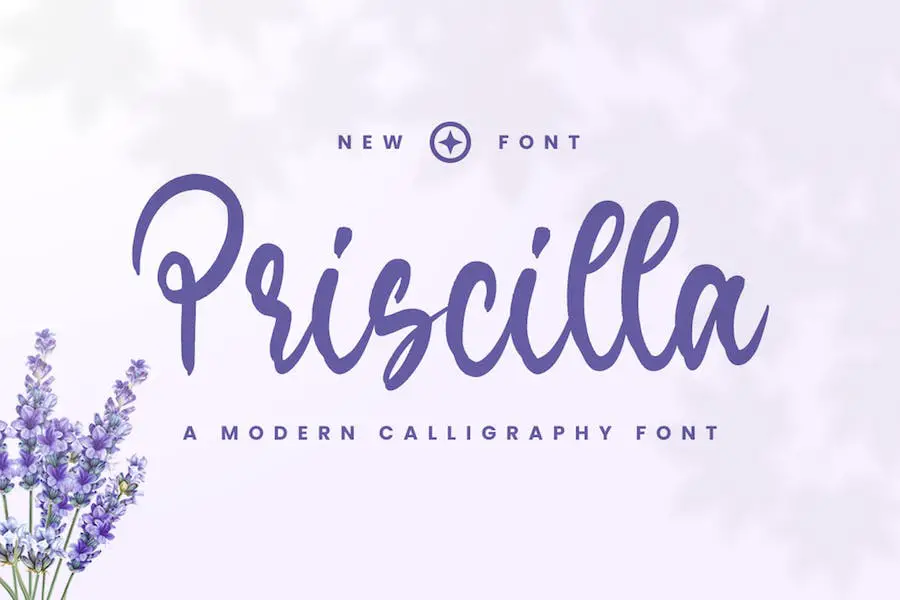
Priscilla 是一種現代而優雅的腳本字體,非常適合徽標、品牌、邀請函和社交媒體帖子等各種應用。
憑藉其精緻的外觀和優雅的風格,Priscilla 一定會讓您的項目脫穎而出。 您可以將它用於婚禮設計、文具等等。 該字體具有 OTF 和 TTF 格式,並包含 PUA 編碼字符,無需額外的設計軟件即可完全訪問。
因此,無論您是平面設計師、營銷人員還是博主,您都會喜歡 Priscilla 的精緻和多功能性。 對於任何想要為自己的工作增添一絲優雅氣息的人來說,這是一個絕佳的選擇。
與 Priscilla 一起,您可以將您的想法轉化為精美的創作,並給您的客戶和觀眾留下深刻的印象。 那麼今天就來嘗試一下吧!
俄克拉荷馬州
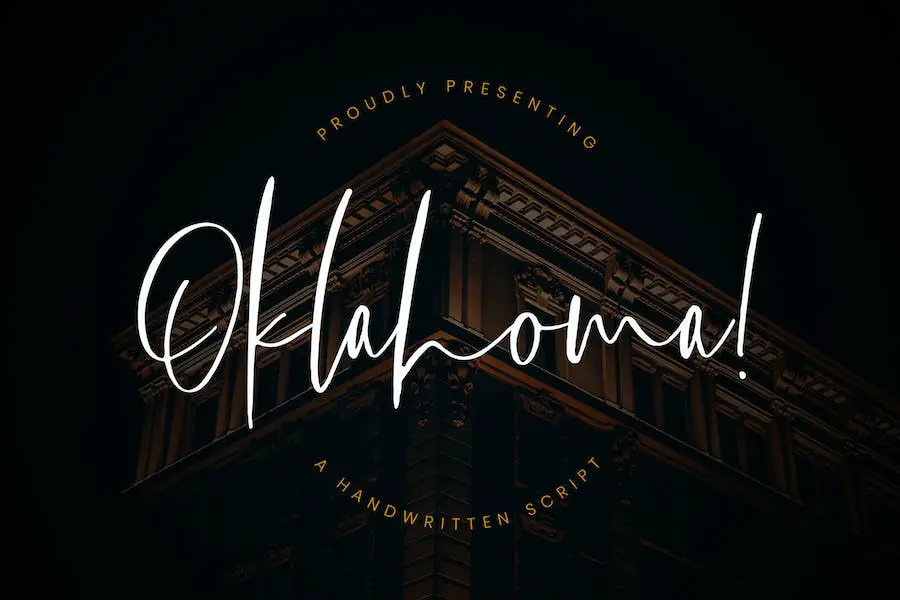
Oklahoma 是一種時尚而現代的字體,為您最新的設計項目增添優雅和優雅的感覺。 它具有自然的手寫腳本和大量的字形和連字,帶來個性化的感覺。
借助多語言支持,您可以使用 Oklahoma 進行各種品牌項目、徽標設計、婚禮請柬、社交媒體帖子、廣告和產品包裝。
無論您是為 Google Instagram 字體、Adobe Instagram 字體、Word Instagram 字體、現代 Instagram 字體還是 Instagram 時尚字體創建內容,Oklahoma 都能提供獨特而精緻的外觀。
雅瑪塔
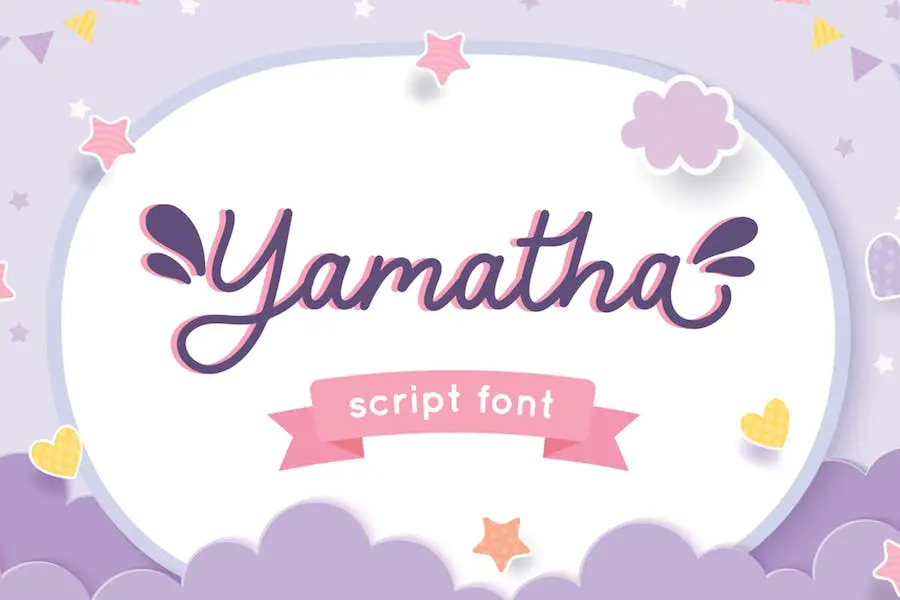
Yamatha 是一種斜體樣式的腳本字體,非常適合為您的設計項目增添額外的優雅氣息。 它的開頭和結尾花體結合在一起使字母更加美麗。 該字體還包括連字和多語言支持。
Yamaha 非常適合婚禮促銷、品牌推廣、徽標、邀請函和文具。 它也非常適合社交媒體帖子、產品包裝、商品、博客設計、遊戲標題、可愛的風格設計以及書籍或封面標題。
對於希望為自己的作品增添一絲精緻和美麗的設計師來說,這種字體是一個不錯的選擇。 憑藉其廣泛的用途和功能,Yamatha 是任何為 Instagram 和其他社交媒體帖子尋找現代時尚字體的人的必備之選。
鹽
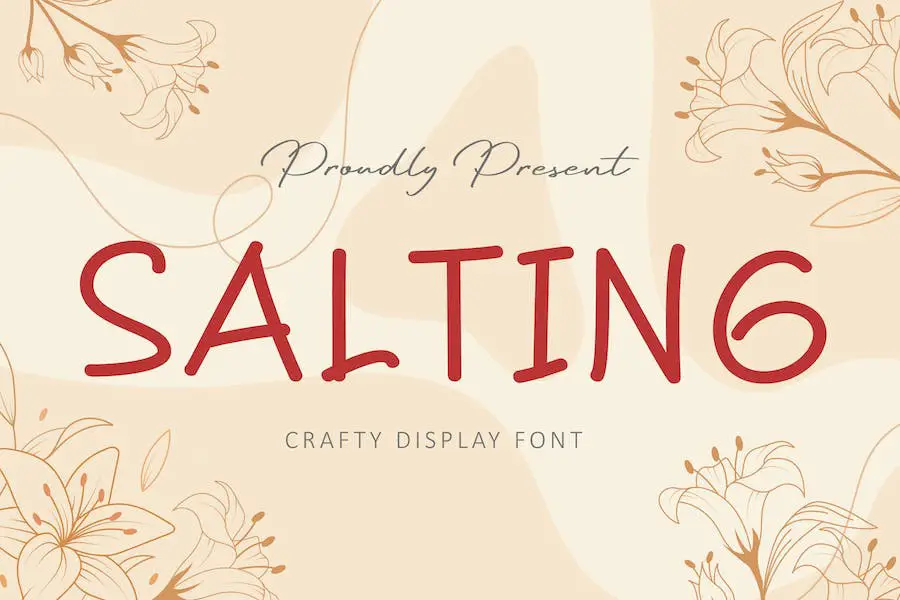
Salting 是一種精緻而奢華的腳本字體,專為社交媒體(尤其是 Instagram)設計。 它是為您的 Instagram 帖子增添優雅氣息、製作令人驚嘆的婚禮請柬或設計精美的文具藝術品的完美選擇。
憑藉其時尚和現代的吸引力,這種字體一定會讓您的內容脫穎而出。
通過 Salting,您將可以使用一系列時尚的字體,這些字體可以輕鬆生成並用於您的 Instagram 帖子。 無論您是在尋找小字體以在標題中容納更多文本,還是想嘗試不同的現代字體,此字體生成器都能滿足您的需求。
貝林多
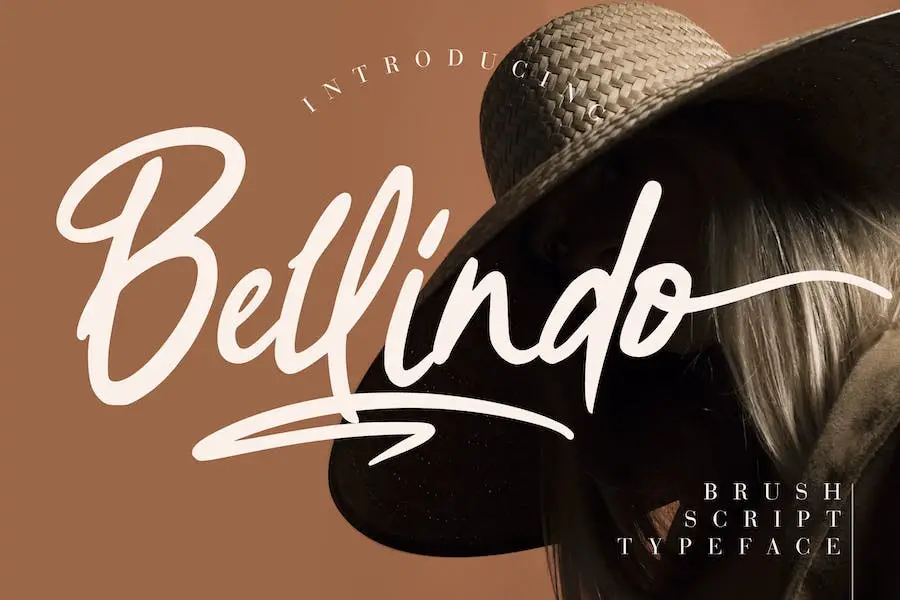
Bellindo 是一種天然的畫筆字體,稱為 It Brush Script,散發著優雅和優雅的氣息。 憑藉其驚人的功能,這種字體非常適合您最新的設計項目。
它完美匹配您的品牌、電影標題、書名、社交媒體、婚禮請柬、卡片以及您能想到的任何其他場合。
您可以享受其令人驚嘆的功能,例如數字、連字、標點符號、花體和標準字符。 此外,您還可以在 Adobe Illustrator、Adobe Photoshop 和 Adobe InDesign 中訪問它。 它還支持多種語言的多語言字符。
嘿比安查
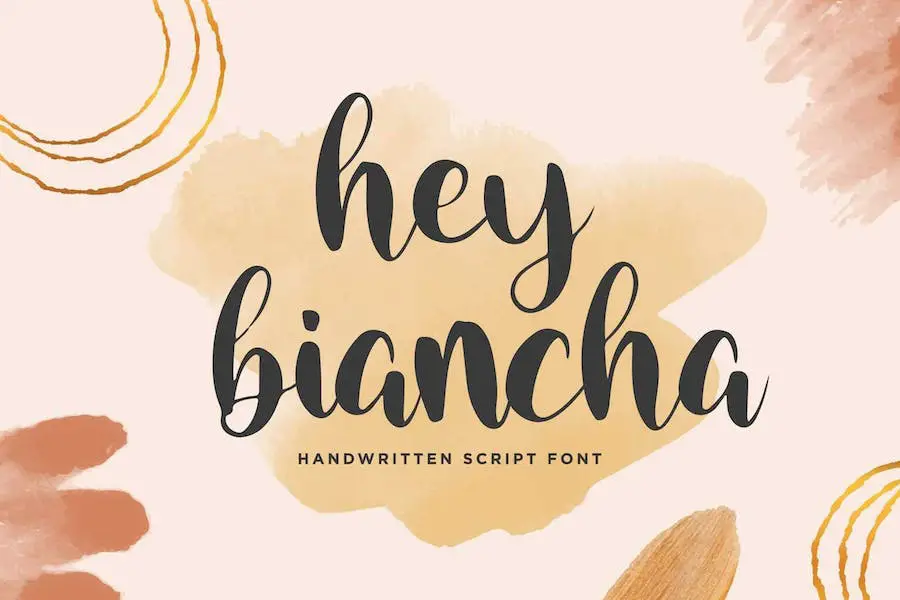
Hey Biancha 是一種手寫腳本字體,非常適合社交媒體帖子、品牌、引言、博客文章、T 卹設計、徽標和邀請函。 憑藉其現代而獨特的風格,在您的項目中使用這種字體將為您的項目帶來引人注目的吸引力。
它提供多語言支持,使您能夠毫無困難地用不同語言定制設計。
使用 Hey Biancha 是一種獨特的方式來改進社交媒體帖子的 Instagram 字體,並創建脫穎而出的現代 Instagram 字體。
其手寫設計為設計增添了個人風格,使其更具吸引力。 嘗試一下 Hey Biancha,用你聰明而富有創意的設計給你的觀眾留下深刻的印象!
卡斯頓維拉
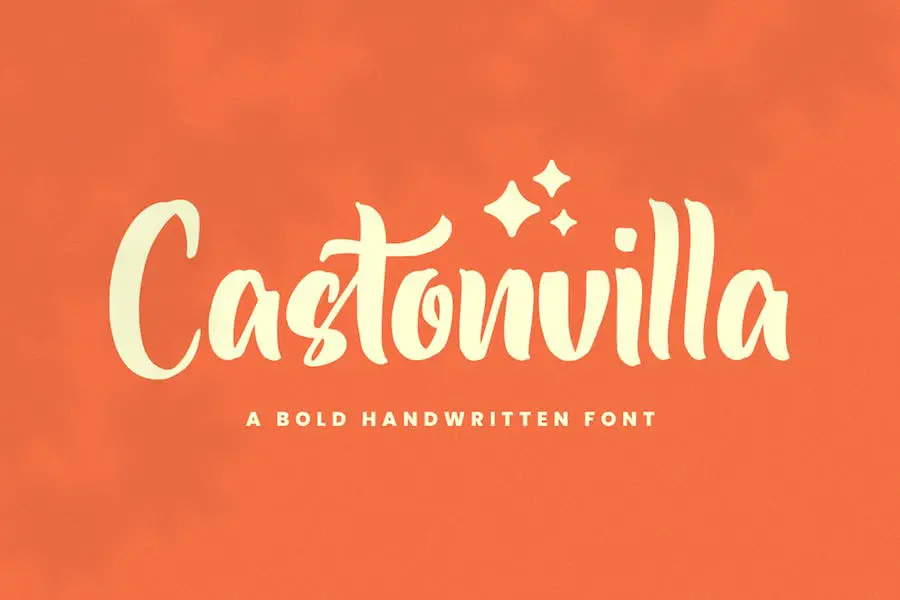
Castonvilla 是尋找時尚現代字體的設計師的完美選擇。 它是一種適合徽標、邀請函、品牌和各種設計項目的腳本字體。
該字體具有精緻、優雅的外觀,非常適合婚禮和社交媒體帖子。 它有 OTF 和 TTF 格式。
少年
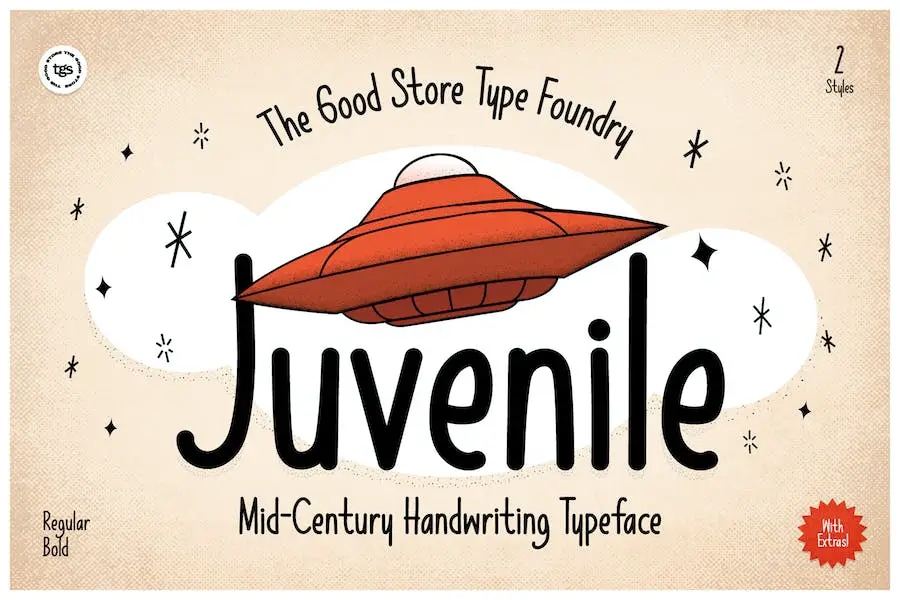
Juvenile 是一種中世紀的手寫顯示字體,將為您的社交媒體帖子增添一絲復古風格。 它有常規和粗體兩種風格,非常適合為女孩創建 Instagram 名稱字體樣式。
手寫顯示的靈感來自 20 世紀 50 年代的青少年手寫風格,為您的設計帶來獨特而真實的感覺。
暖色調
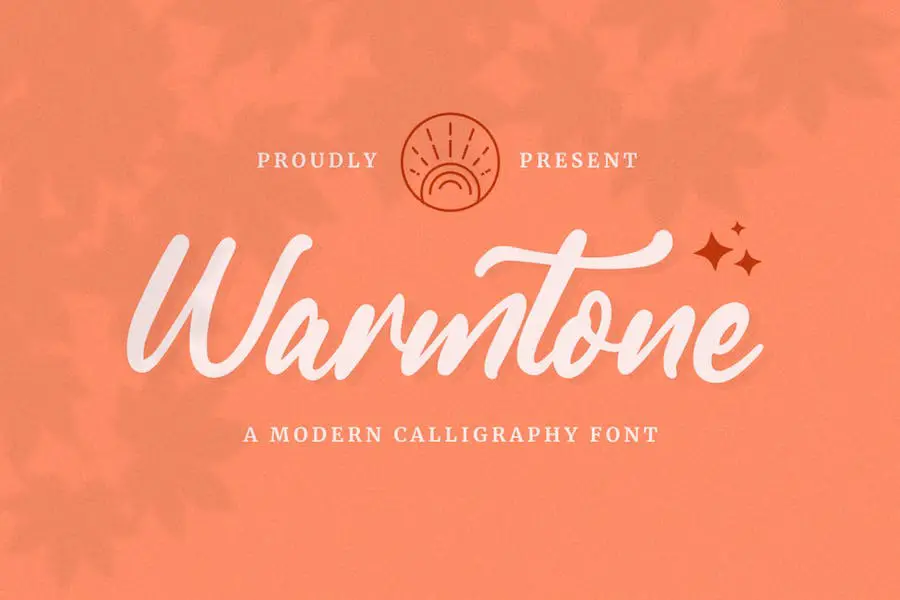
Warmtone 是一種優雅的腳本字體,非常適合品牌推廣、文具店、婚禮設計和社交媒體帖子。 其精緻的外觀可用於多種用途,是一種多功能的選擇。
正在尋找用於社交媒體帖子的 Instagram 字體? 暖色調是時尚的選擇。 想要使用 Adobe Instagram 字體? Warmtone 採用 PUA 編碼,無需額外的設計軟件即可完全訪問。
Warmtone 體現了溫暖和風格,是任何設計師字體集合的絕佳補充。
波利納劇院
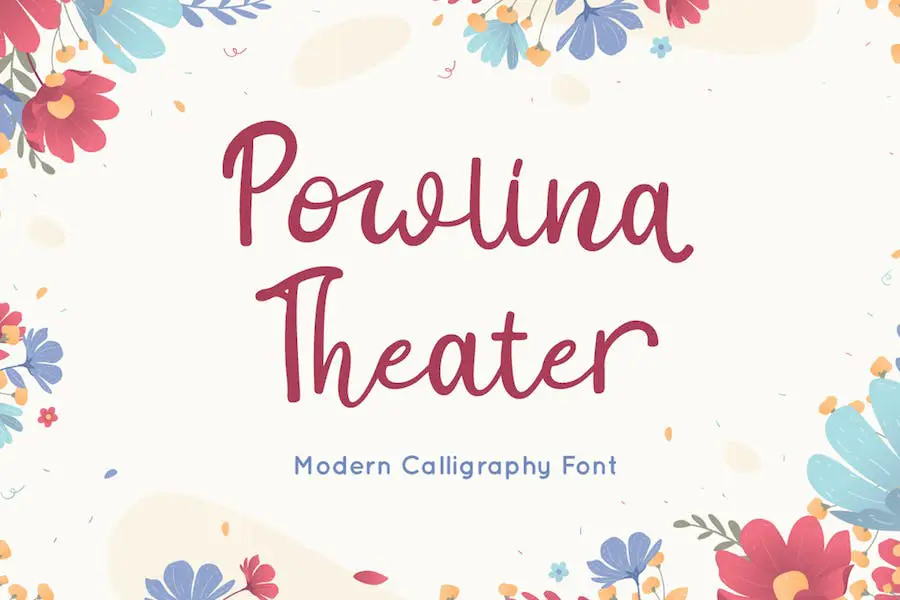
Powlina Theater 是適合您的婚禮及其他場合的完美現代書法字體。 憑藉其多功能的風格,您可以創建令人驚嘆的設計,使您的項目脫穎而出。
該字體附帶各種風格集和連字,允許您自定義和增強您的設計。 它支持多種語言,使其易於訪問並適合全球項目。
無論您是在設計品牌、徽標、請柬、報價、婚禮請柬還是包裝,Powlina Theater 都會為您的創作增添一絲優雅和精緻。 它也非常適合 Cricut 和輪廓字體,讓您將您的設計提升到一個新的水平。
叢林
Jungle 是一款令人驚嘆的手刷字體,它抓住了樂趣和簡單的本質。 受到兒童書籍和街頭手繪字體的啟發,這種字體非常適合您最新的設計項目。
無論您需要電影標題、徽標、社交媒體帖子還是婚禮邀請函的字體,Jungle 都會讓您的項目看起來棒極了。 它可以在 Adobe Illustrator、Photoshop 和 InDesign 中訪問,因此用途極其廣泛。
該字體還包括數字、連字,並支持多種語言,使其適用於多種場合。
它具有 OTF、TTF 和 WOFF 格式,確保與不同平台的兼容性。 憑藉 PUA 編碼字符,Jungle 無需額外的設計軟件即可完全訪問。
此外,它還配有標準字符和花體,可為您的設計增添額外的創造力。 那為什麼還要等呢? 使用 Jungle 為您的項目帶來有趣且獨特的外觀!
你好桑蒂尼
Hello Santtiny 是一種粗筆腳本字體,可為您的創意項目增添一絲戲劇性和風格。 該字體與 PC 和 Mac 兼容,可在 Adobe Illustrator、Adobe Photoshop、Adobe InDesign 甚至 Microsoft Word 等各種平台上訪問。
Hello Santiny 的一大特色是它的網絡字體功能,讓您可以輕鬆地在網站和在線平台上使用它。 此外,該字體包含 PUA 編碼字符,這意味著您無需額外的設計軟件即可訪問其所有功能。
Hello Santtiny 還提供多語言支持,使其適合需要特殊字符(例如 a、o、u、ä、O、U、ß、 和 )的項目。 通過包含連字,該字體為您的設計提供了更多的多功能性和样式選項。
加斯頓
GASTON 是一款纖細的無襯線字體,非常適合 Instagram 業務。 它提供了獨特的風格,可以輕鬆匹配各種項目,如徽標、包裝、廣告和可愛的雜誌。
通過將 GASTON 融入您的創意中,您會注意到它如何使它們脫穎而出並吸引觀眾的注意力。
無論您是在為您的 Instagram 名稱尋找小字體、數字字體還是時尚字體,GASTON 都能滿足您的需求。 嘗試一下,看看它如何提升您的設計遊戲!
卡利納
Kallina 是一款手刷時尚腳本字體,名為“It Hand Brush Stylish”。 這款現代 Instagram 字體非常適合為您的項目增添一抹風格和獨特性。
雖然您可以在 Instagram 上使用幾乎任何您喜歡的字體,但某些字體可能不像其他字體那麼容易閱讀,尤其是在較小的屏幕上。
因此,如果您想確保您的帖子清晰易讀且可供廣大受眾訪問,建議您堅持使用更常用且易於閱讀的字體。
為 Instagram 帖子選擇正確的字體可能取決於個人喜好,但必須考慮易讀性、可見性以及與您的品牌或個人風格的一致性等因素。
嘗試不同的字體,看看哪種字體最適合傳達您想要向關注者傳達的信息或風格。